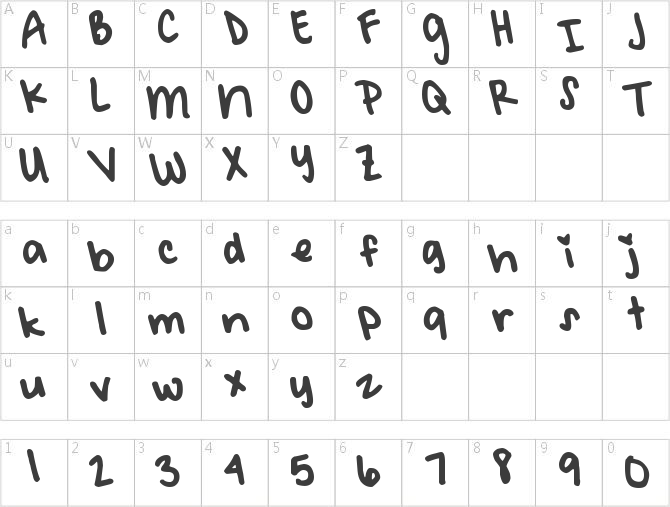
DJB Meet Me at My Locker
DJB Meet Me at My Locker介紹
DJB Meet Me at My Locker字體字庫是一款讓人賞心悅目、百看不厭的英文字體,適合各類廣告和產品包裝設計應用,字體大小0.05MB,格式為ttf字體,上傳用戶是蕪耆蕪,作者/版權方為未知